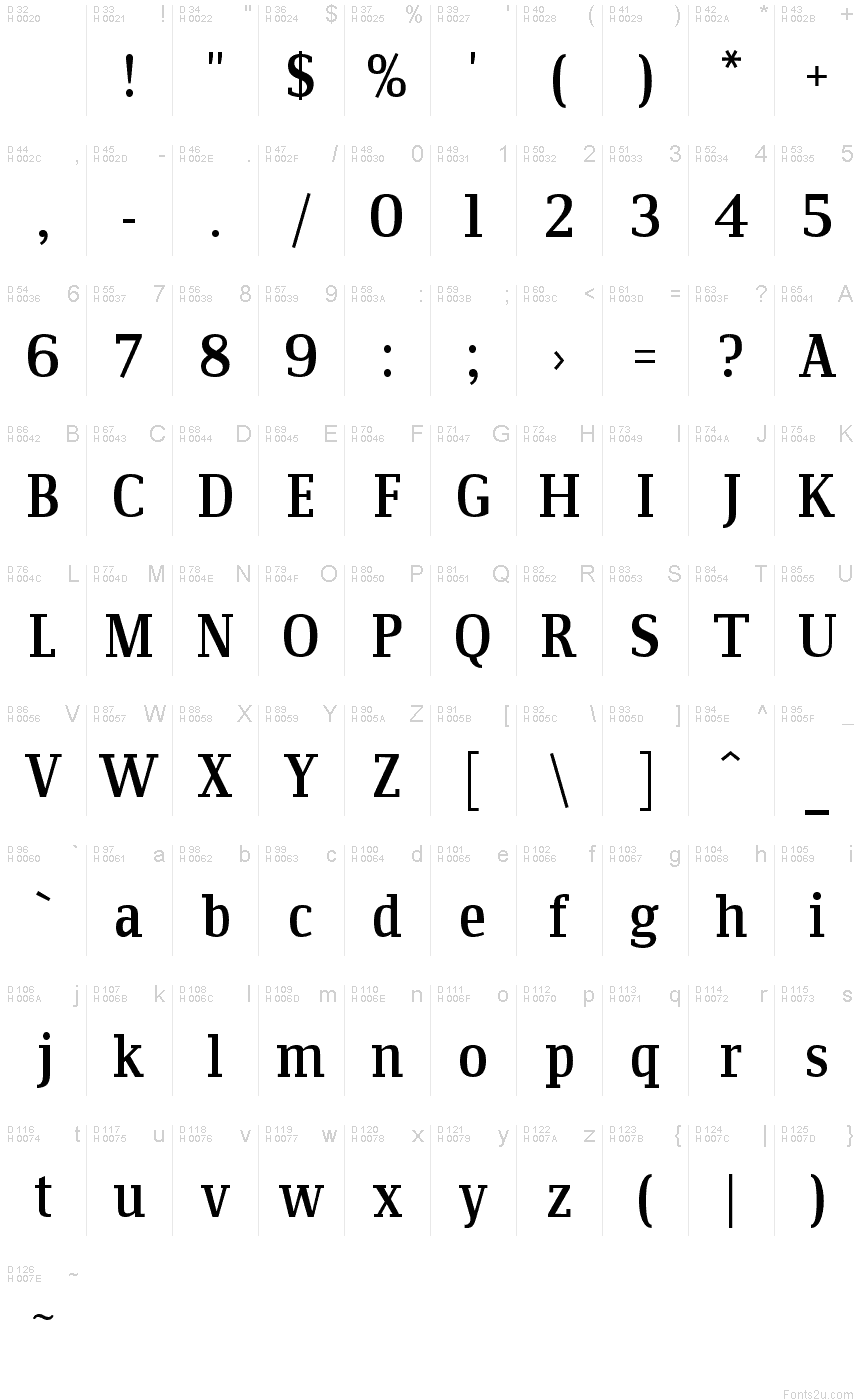
يُعد خط Communist من تصميم Jeroen Klaver من استوديو Shamrock Int. خطاً مجانياً بنظام "سيريف" (serif) يتميز بالطابع المتين والمباشر للمنشورات السياسية القديمة. حروفه مدمجة وداكنة، مع زوائد واضحة وإيقاع ثابت يقرأ كصوت حازم على الصفحة. عند استخدامه بأحجام كبيرة، يبدو النص ثقيلاً ومقصوداً، مما يمنح العناوين والبيانات ملمساً راسخاً يكاد يشبه الطباعة التقليدية.
يتألق خط Communist المجاني هذا في ملصقات الاحتجاج، والتنسيقات التحريرية، والبيانات، وأغلفة الكتب والمجلات المستقلة (Zines)، وعناوين الأفلام الوثائقية، ورسومات الحملات الجريئة حيث تريد أن تشعر بجدية الكلمات وصدقها. التباعد الضيق يجعل العبارات مؤثرة، بينما تظل الخطوط القوية واضحة على الشاشات وفي الطباعة الخشنة. نسّق Communist مع خط هندسي بسيط بلا زوائد (sans serif) للنصوص الفرعية أو النصوص الأساسية لتحقيق التوازن مع طاقته الكثيفة والعملية.